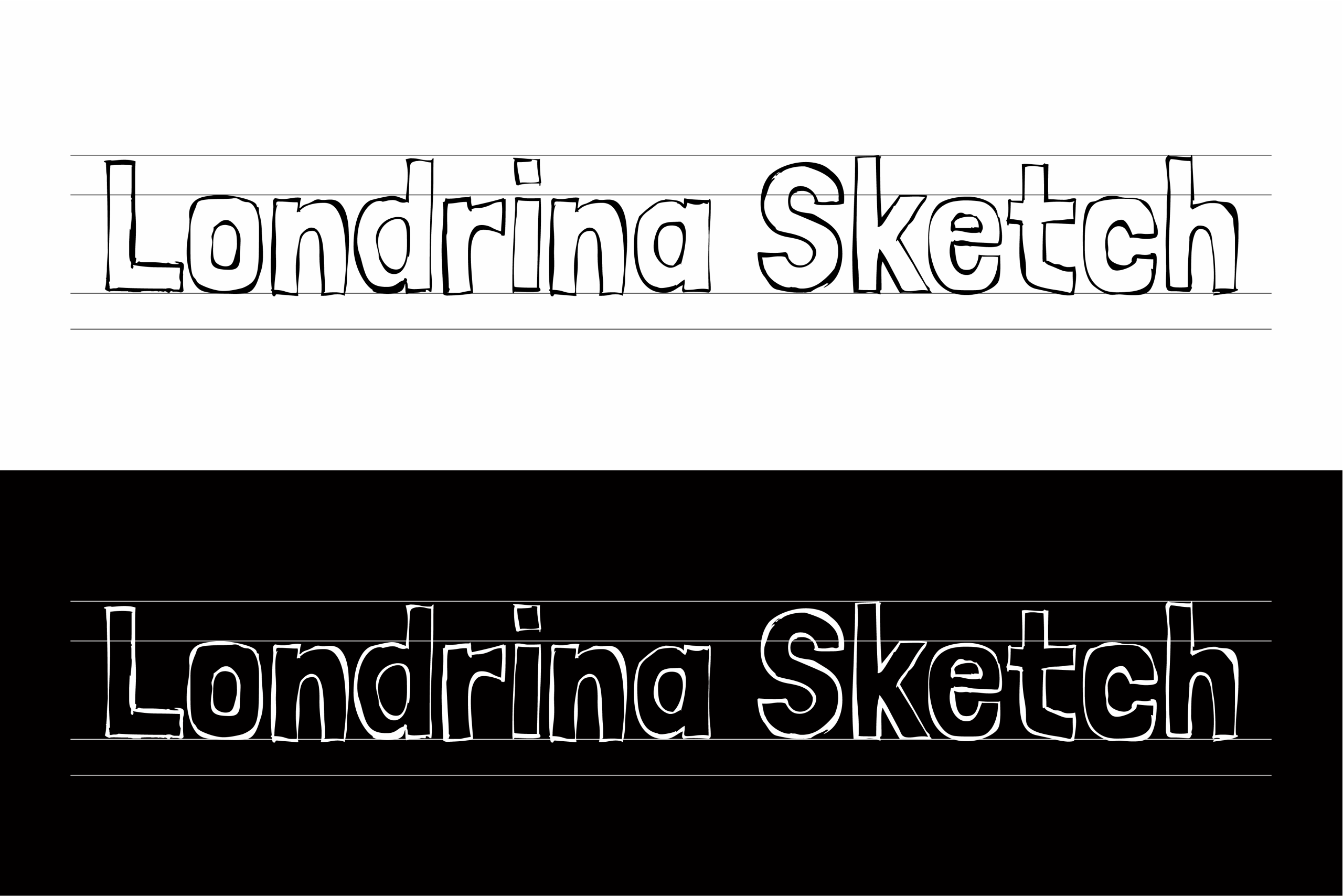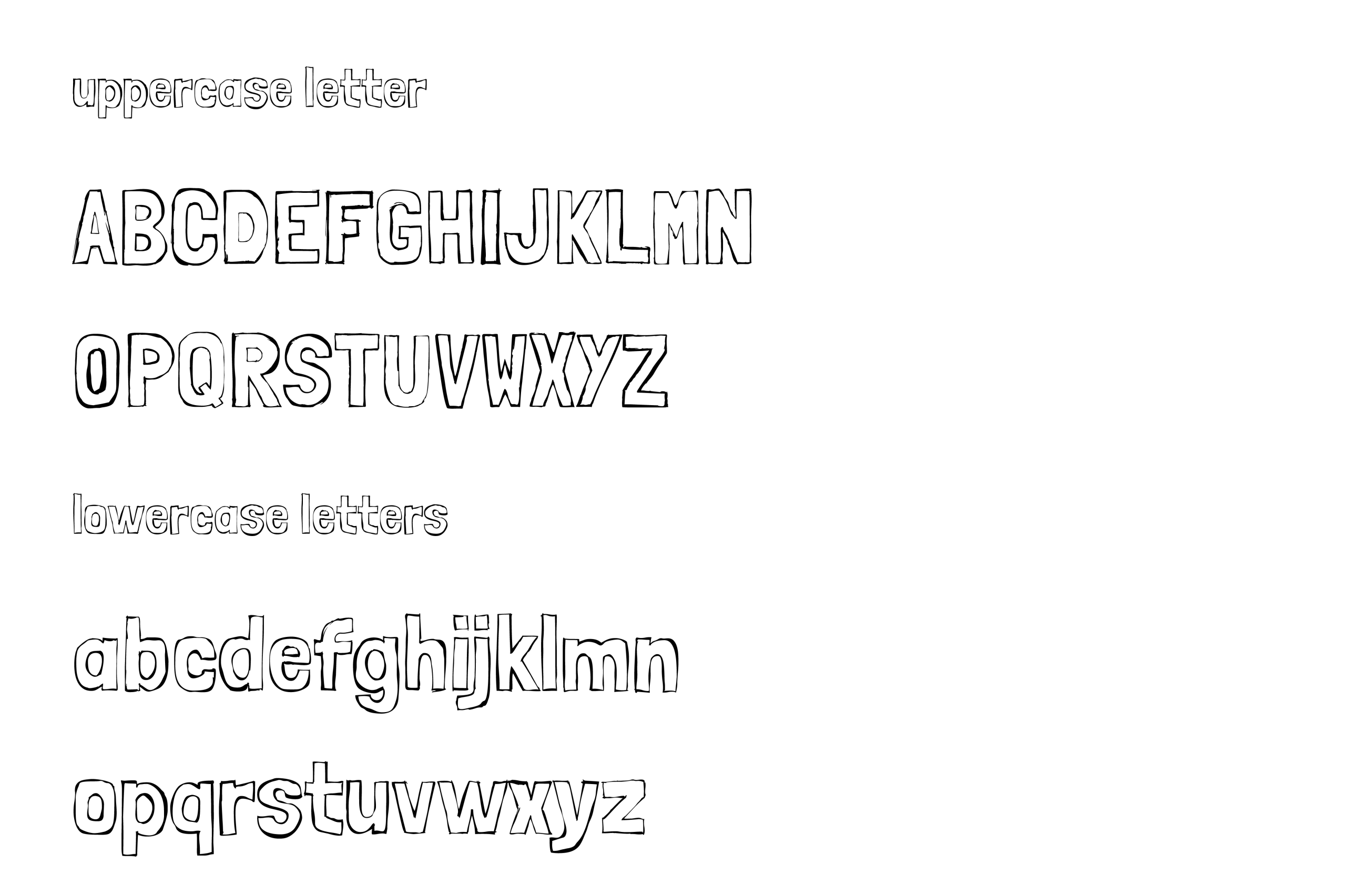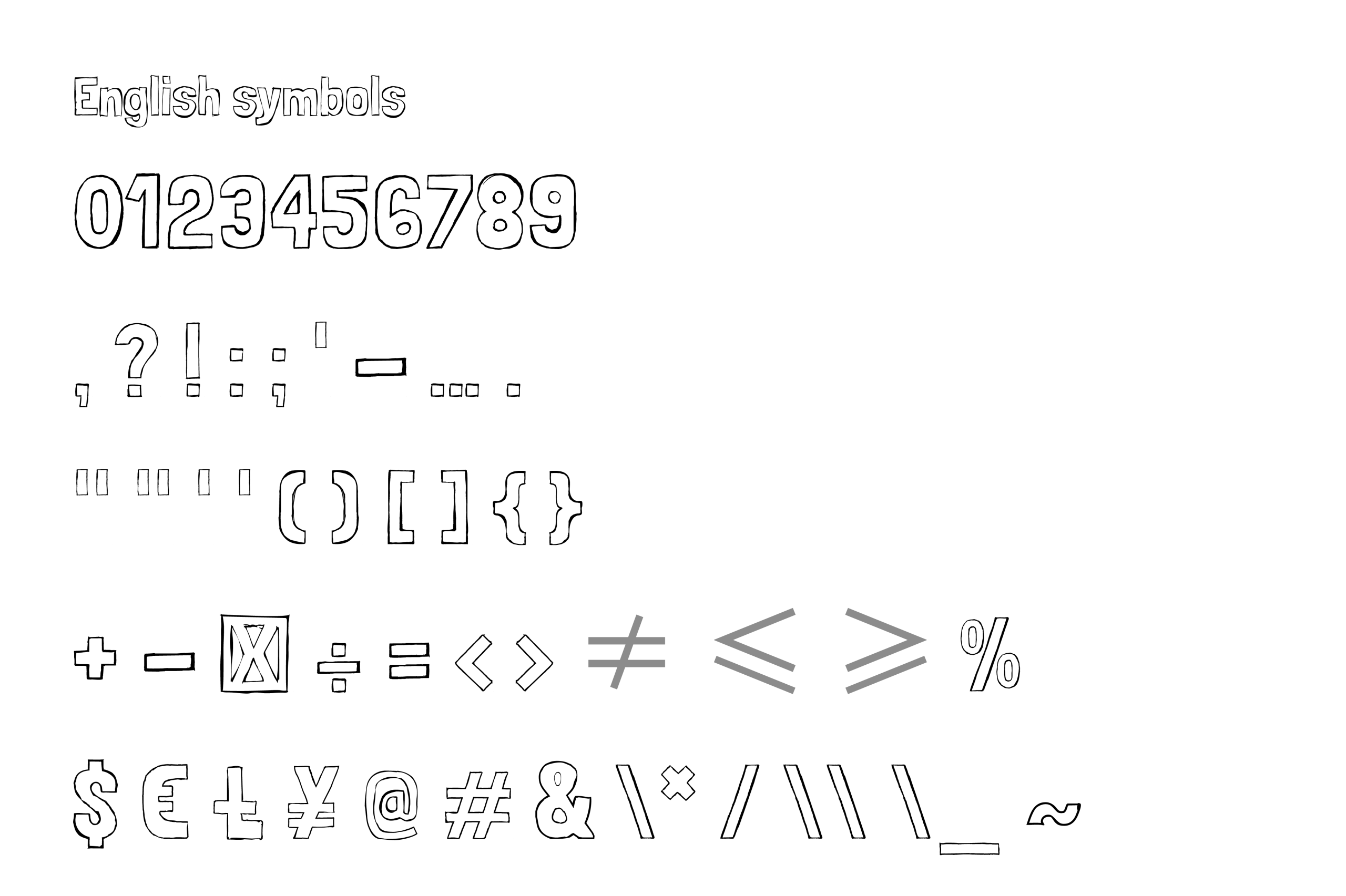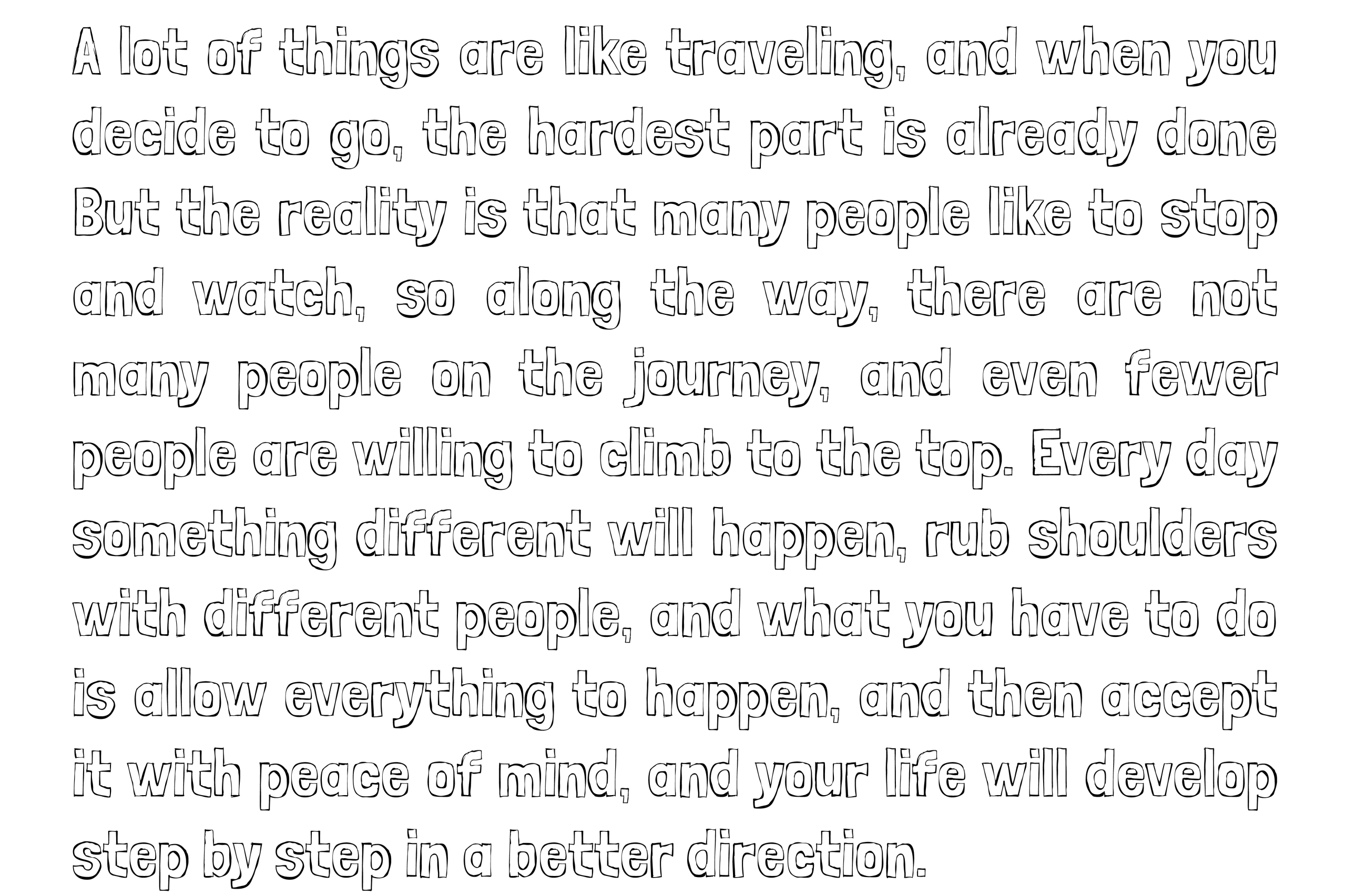
Londrina Sketch
Londrina 是一款由字体设计师 Marcelo Magalhães 设计的创意英文字体。字体最初从方格纸上的手工绘字开始,设计师先以纸笔绘制字母,再通过描图纸重新描摹和调整字形,在保留手工绘制痕迹的同时逐渐形成完整的字体系统。相比经过严格几何规范处理的现代无衬线字体,Londrina 更强调自然、随性和富有个性的字形表现,整体呈现出一种轻松而鲜活的视觉气质。
Londrina 的设计灵感来自日常生活中十分常见的街头商业文字和店铺招牌。咖啡馆、街边商店以及城市商业空间中的手绘字样,往往没有经过高度标准化的字体设计,却因为笔画和轮廓中保留了人的书写痕迹,而具有非常直接的亲和力。Londrina 正是将这种朴素的街头文字感转化为数字字体,通过无衬线结构结合手绘轮廓,使字母既保持清晰的识别度,又不会显得过于规整和机械。
从字形来看,Londrina 最大的特点是具有明显的轮廓感。字母整体较为饱满,笔画结构简洁,转角和曲线处理相对圆润,同时在不同字母之间保留了一些自然的变化。这样的设计让字体看起来不像经过精密计算的标准化字库,而更像是设计师亲手绘制出来的文字。尤其在大字号展示时,字母外轮廓所呈现出的轻微不规则感会更加明显,也使 Londrina 拥有非常鲜明的视觉辨识度。
Londrina 的另一项特点是兼具童趣与复古招牌感。它的字形并不会给人传统手写字体那种明显的书写方向和连笔效果,而是以相对完整、厚实的字母结构为基础,通过轮廓变化制造手绘感。因此,它既能够用于具有复古气质的视觉设计,也可以融入年轻、活泼甚至略带趣味性的现代作品中。这种介于街头招牌、手工字体和现代展示字体之间的风格,也让 Londrina 在同类英文字体中拥有较高的辨识度。
在实际使用时,Londrina 更适合作为标题字体和展示字体。较大的字号能够充分展现其独特的字形轮廓,因此非常适合海报标题、品牌名称、活动视觉、包装设计以及宣传物料等场景。在餐饮、咖啡、生活方式、儿童产品和创意品牌的视觉设计中,Londrina 所具有的亲切感和手工气息也能够很好地传递轻松、自然的品牌调性。如果用于插画、社交媒体配图或短句设计,则可以进一步利用它较强的字形个性,让文字本身成为画面中的视觉元素。
为了适应不同的设计需求,Londrina 还发展出了不同的字体版本,包括 Londrina Solid、Londrina Layer 和 SVG Color。Solid 版本强调完整而醒目的实心字形,适合直接用于标题和主视觉;Layer 版本则通过字体图层的组合增加了更多装饰和变化空间,可以根据不同设计需求进行叠加使用;SVG Color 版本则进一步扩展了字体的色彩表现能力,为数字设计和创意视觉提供了更加丰富的使用方式。不同版本虽然在表现形式上有所区别,但都延续了 Londrina 原本轻松、手绘和富有街头气息的设计特点。
Londrina 最初的字体名称为 Folk,后来由于名称已经被其他字体厂商使用,在字体加入 Google Fonts 字体目录时进行了重新命名,最终采用 Londrina 这一名称。设计师以自己曾经生活过的城市作为字体的新名称,也让这款字体从单纯的字形设计拥有了一层更加个人化的创作背景。字体本身并没有因此改变原有的设计方向,依然延续着最初从街头商业文字和手工绘字中获得的灵感。
整体而言,Londrina 是一款非常有性格的手绘风格英文字体。它没有刻意追求字体结构上的绝对统一,而是通过人工绘制所产生的自然变化,让原本简单的英文字母拥有更加鲜明的情绪和温度。圆润饱满的字形、略带不规则感的轮廓以及源自街头招牌的设计灵感,共同构成了 Londrina 独特的视觉风格。对于喜欢手绘字体、复古招牌字体和创意英文字体的设计师来说,Londrina 是一款兼具辨识度与实用性的免费开源字体,尤其适合需要突出个性和视觉氛围的标题、品牌与海报设计。